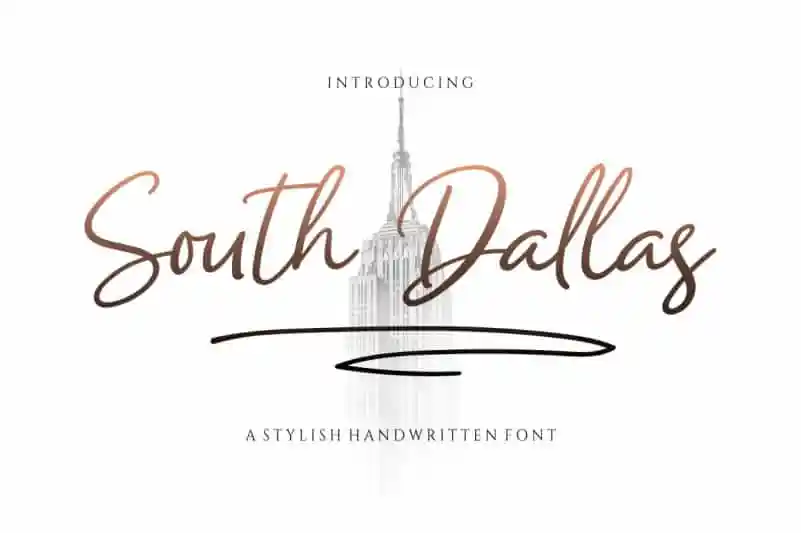
South Dallas Script Font – Download Grátis
A South Dallas Script Font é uma elegante fónta para escrita manuscrita que captura a sofisticação dos autocolagens feitas à mão no sul de Dallas, Texas. Seu fluxo denso fino e suave permite criar textos não apenas profissionais, mas também repleto de personalidade e charme. A sua característica mais intrigante é o tom delicado e elegante que reflete a elegância e o encanto da cultura autocolagem dos Estados Unidos. Perfeita para designers que buscam trazer uma atmosfera única e sofisticada a seus projetos, esta fónta escrita à mão oferece um toque único de criatividade e estilo.